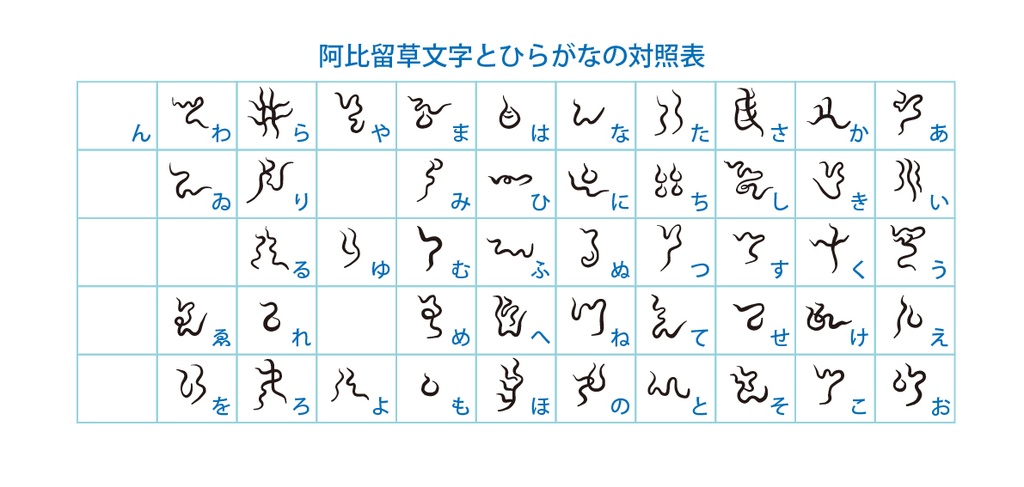
デジタルコンテンツ 阿比留草文字フォント
神代文字のひとつ、阿比留草(あひるくさ)文字のフォントです。阿比留草文字は、各地の神社において神璽や守符、奉納文などに用いられている文字です。 WindowsやMacで使用できるOpenTypeフォントです。 ひらがなを阿比留草文字におきかえられます。 【収録文字】 ひらがな あいうえお かきくけこ さしすせそ たちつてと なにぬねの はひふへほ まみむめも やゆよ らりるれろ わゐゑを 【データ内容・使用方法】 zipファイルを解凍してください。 OTFファイル pkahirukusa3-Regular.otf JPGファイル(文字表示の見本) font-sample.jpg テキストファイル readme.txt が収録されています。 pkahirukusa3-Regular.otf をインストールしてください。 【購入の際の注意点】 商用利用OKです。 使用した場合、ご一報いただけるとうれしいです。Twitterなどで紹介します。 フォントファイルの改変・再配布は禁止です。